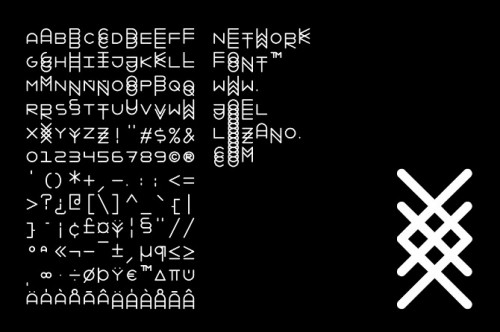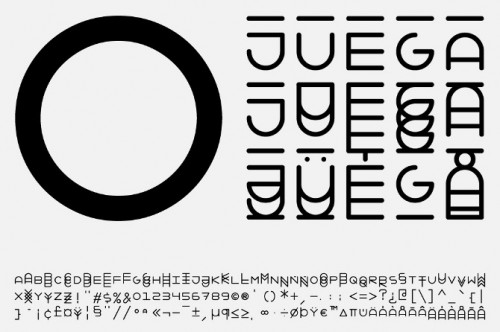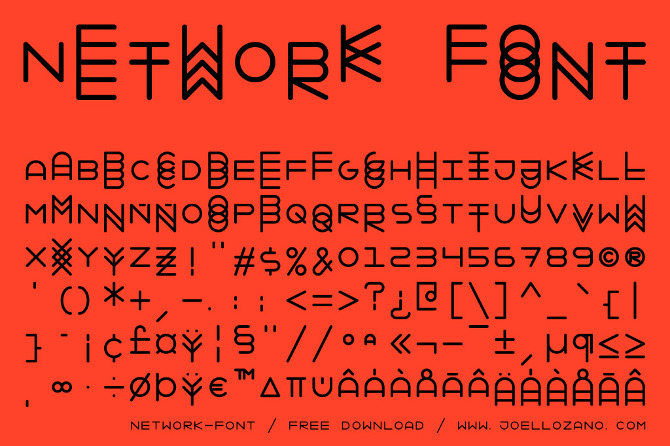
Font Design: Network Font
Il Font Design di oggi è: Network Font (download)
Network Font, basato sull’impostazione di spaziatura fissa, è stato realizzato nel 2011 da Joel Lozano che ha deciso di rilasciare il font sotto licenza gratuita e perciò liberamente scaricabile da tutti.
La particolarità di questo font sono senz’altro le maiuscole che appaiono ripetute in orizzontale, questo crea alla percezione dell’utente l’effetto “mal di testa” dopo una prolungata visualizzazione della scritta.